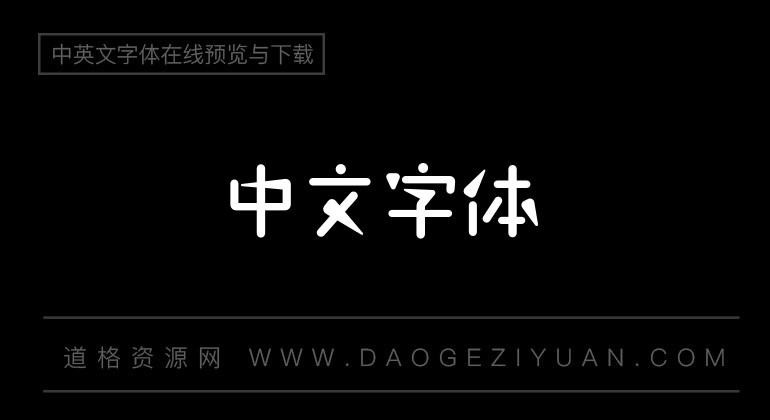
A-OTF タカモダン Min M
? A-OTF タカモダン Min M 字体是一款由日本排版公司タカモダン设计的日本汉字字体,它拥有独特的设计风格,汉字笔画细腻,拥有较强的抗锯齿能力,可以清晰地显示汉字的细节,使汉字显得更加立体,给人以极好的视觉效果。它还支持多种编码,可以满足不同客户的需求。
A-OTF タカモダン Min M是一款非常不错的手写艺术字体,具有很好的视觉感,适合于文化类的宣传设计、商业类品牌的广告和产品包装设计以及个性化文字排版等较多场景。
A-OTF タカモダン Min M字符映射图